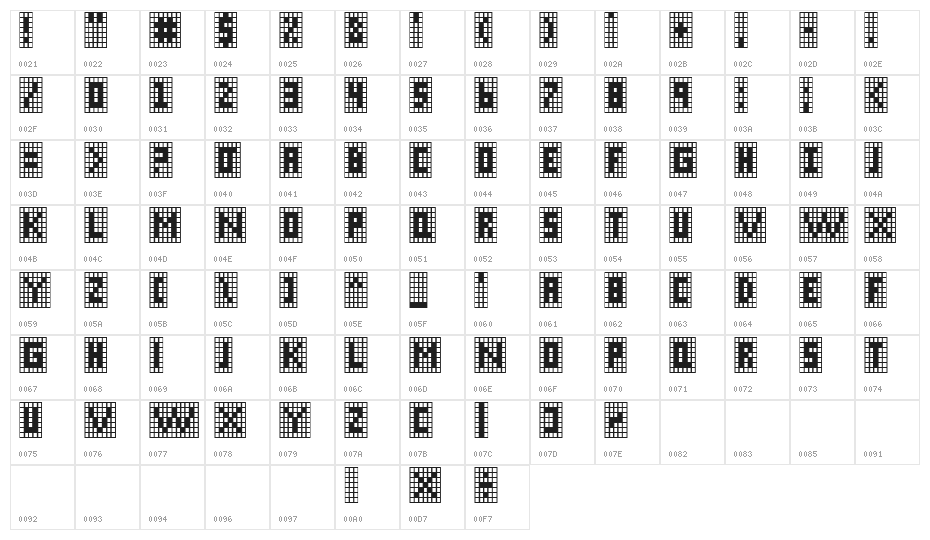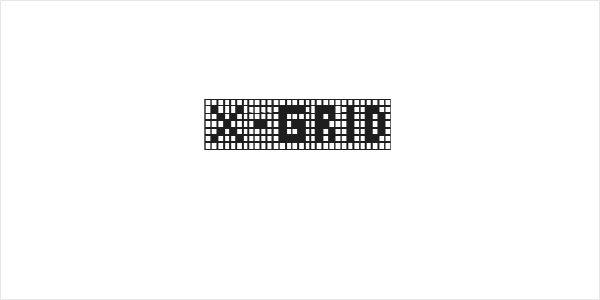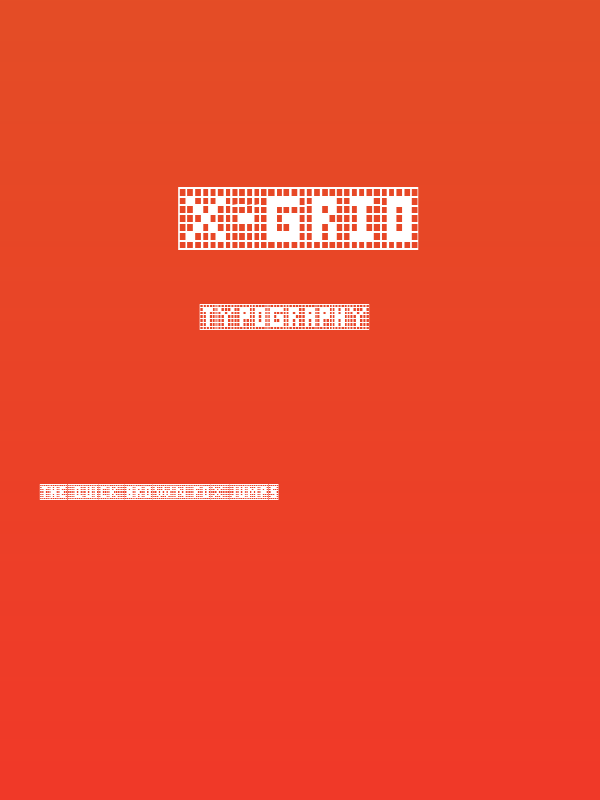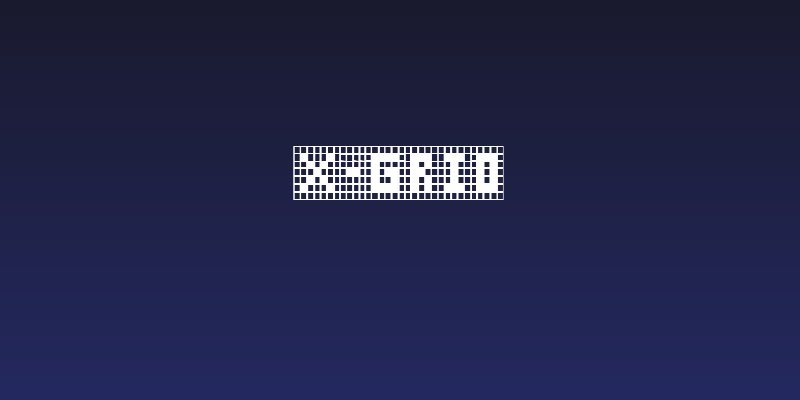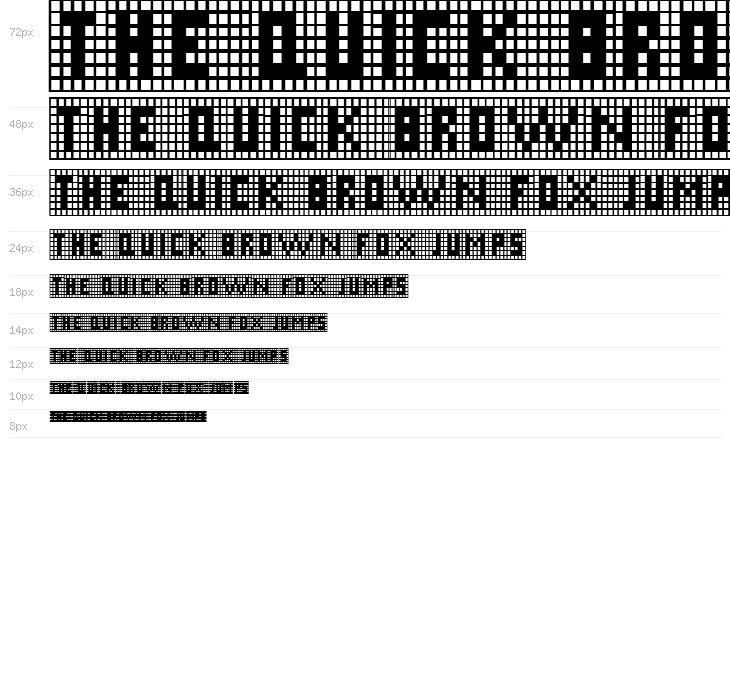
X-Grid Font
Fonts by Daniel Zadorozny - www.iconian.com
| Caso d'uso | Logos, Headlines, Digital displays |
| Progetti proposti | Ideal for digital displays, retro-themed designs, video game graphics, and tech-related branding. |